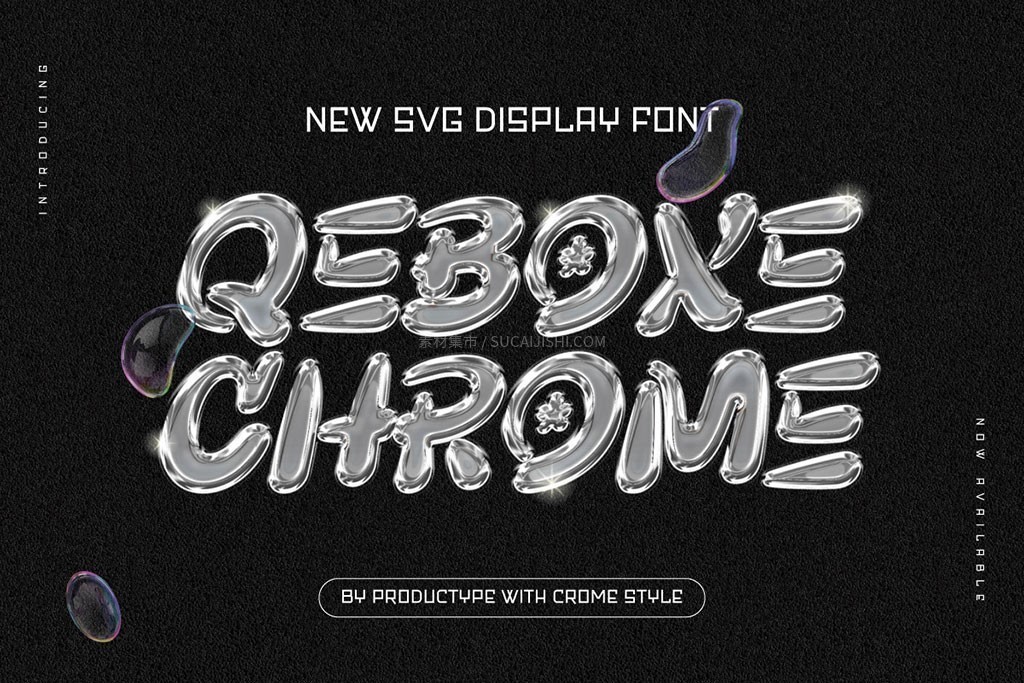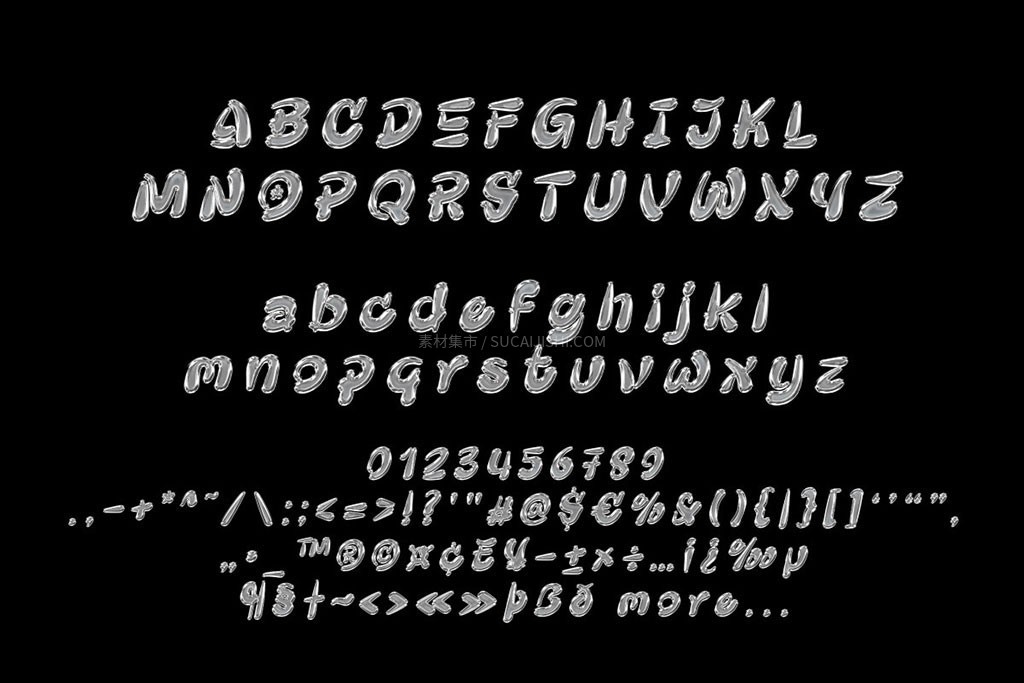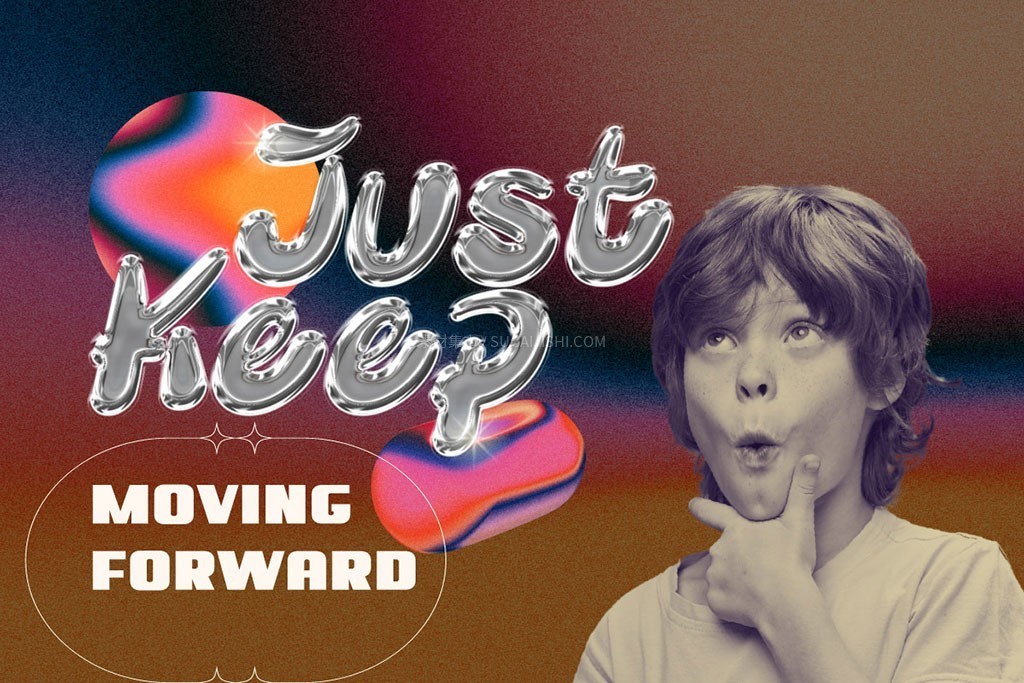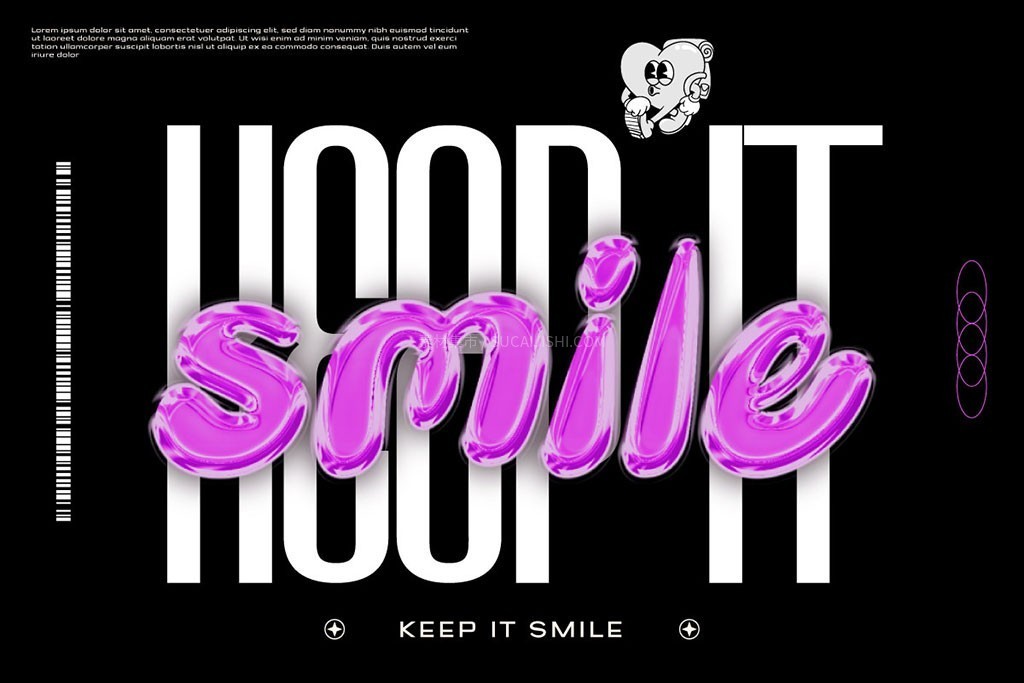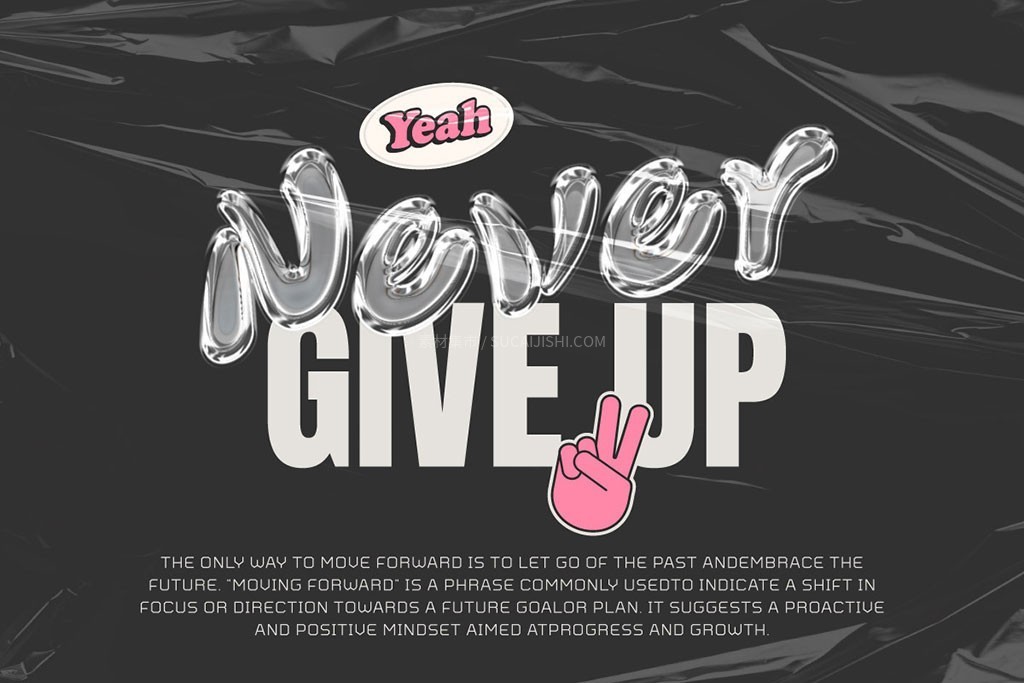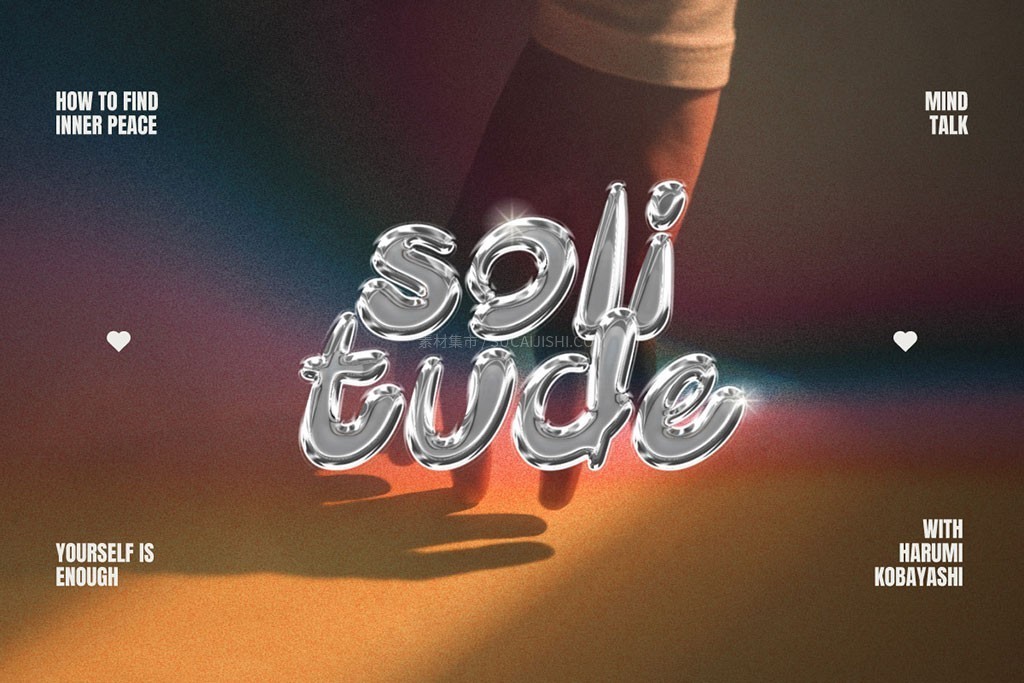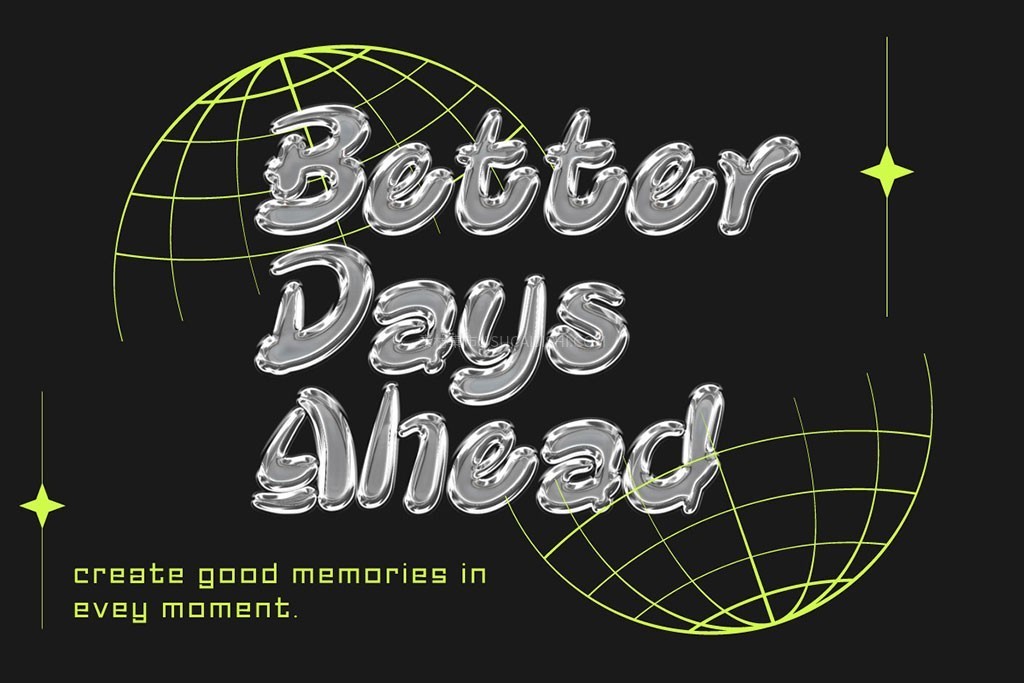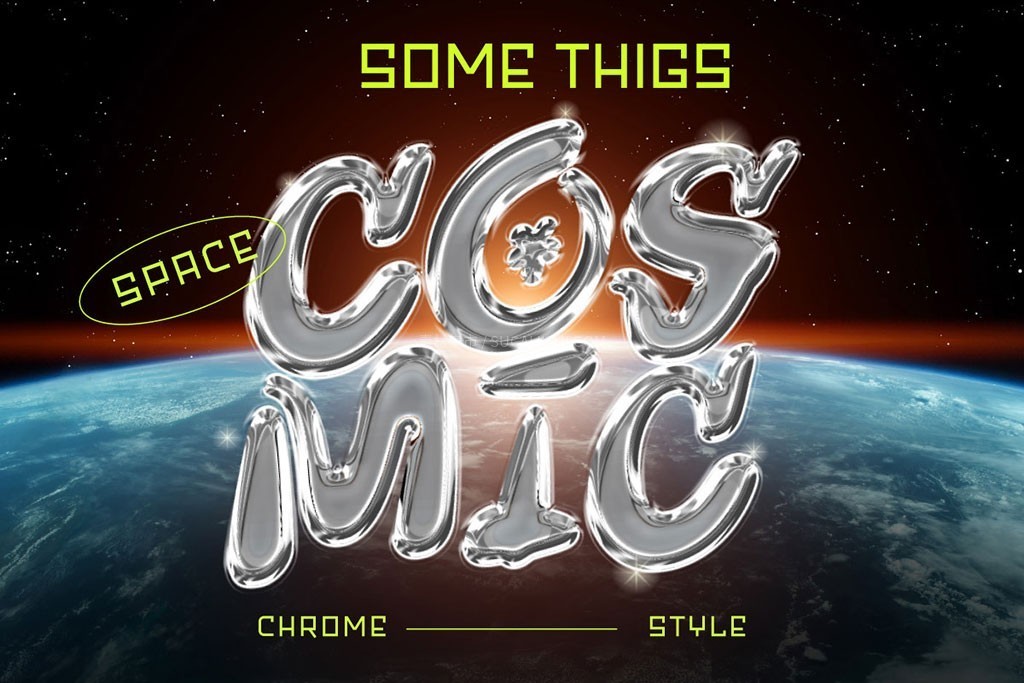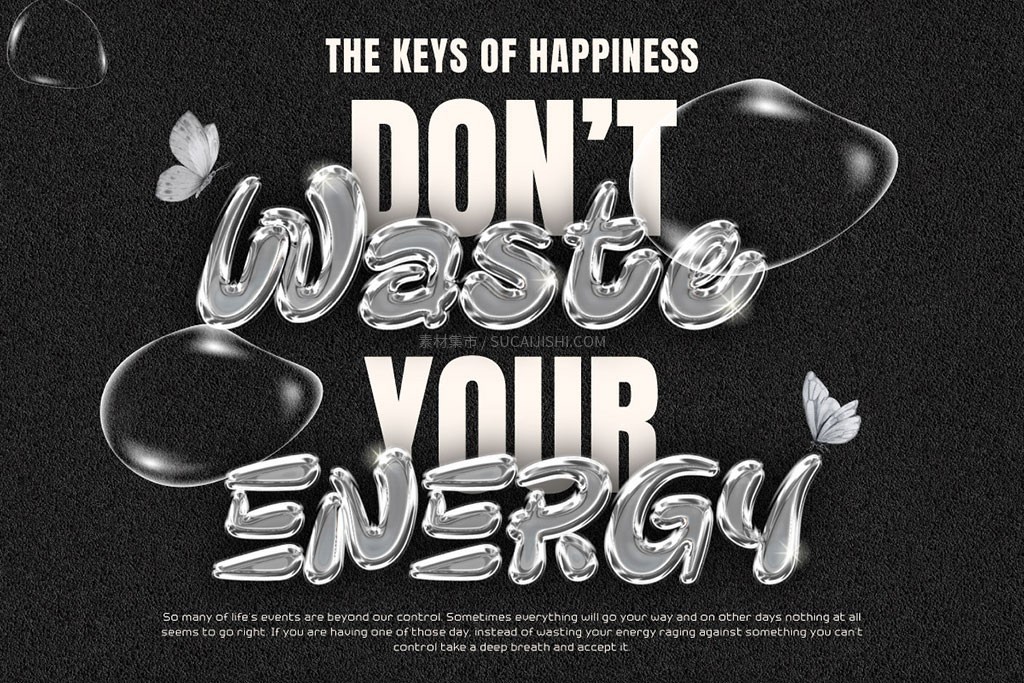
Qebox Chrome 3D镀铬风格SVG字体
Qebox Chrome 是一款充满未来感与大胆元素的3D镀铬风格SVG字体。它采用先进的SVG技术,呈现出高分辨率和逼真的光影细节,让每个字母都闪耀着极具视觉冲击力的金属光泽。该字体包含 OTF 和 TTF 格式,支持 PUA 编码与多语言,无需额外设计软件即可访问基础字符。为了获得最佳体验并调用所有字形变体,建议在支持 OpenType 功能的专业软件中使用。